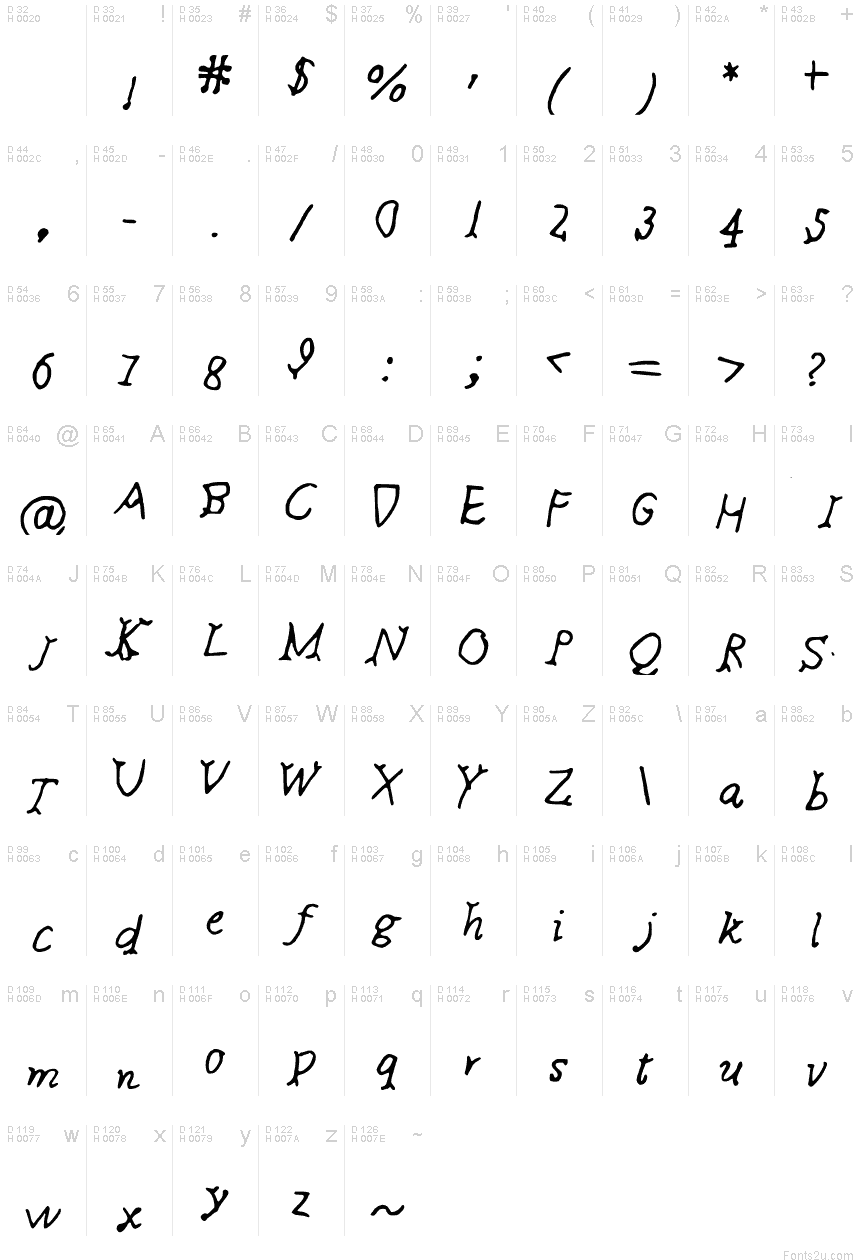
Swerve, vytvořené studiem MyScriptFont, je bezplatné ručně psané písmo s uvolněným, skloněným rytmem a lehkým nádechem poloviny minulého století. Písmena se pohupují od širokých křivek do rychlých ostrých obratů, mají zaoblené konce a lehce štětcový dojem, díky čemuž působí linka hřejivě a nikoliv upjatě.
Hodí se pro neformální branding, menu v kavárnách, titulky na plakátech, přáníčka nebo obaly ve stylu scrapbooku, kde na lidském tahu záleží víc než na dokonalosti. Jako bezplatné písmo funguje skvěle i na obálky, titulní karty a krátké citáty – vlnité spoje a prostorné křivky dodají i několika málo slovům živý a bezprostřední náboj.
Swerve